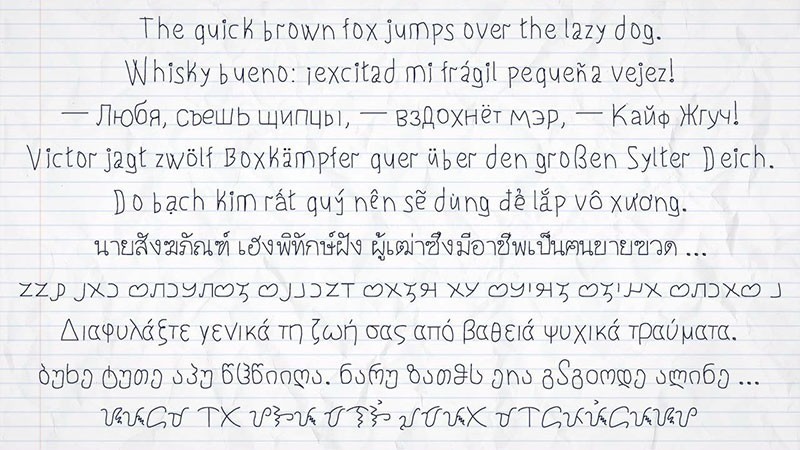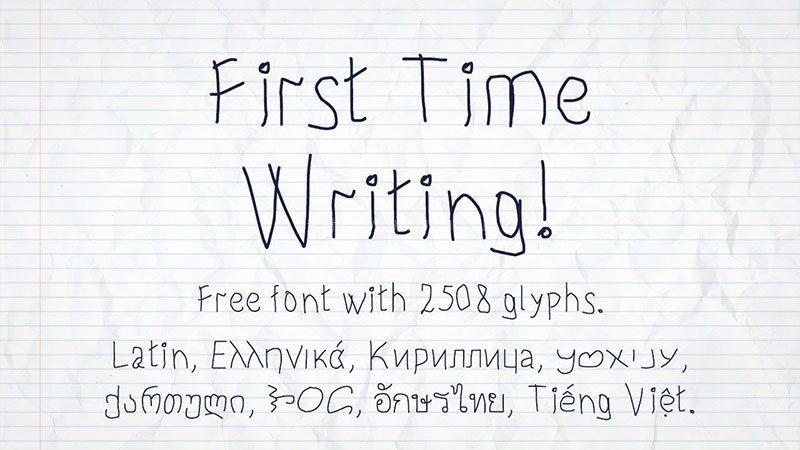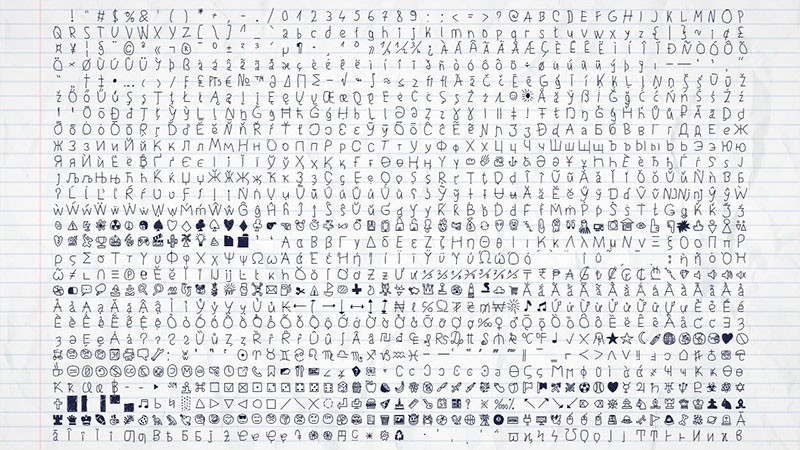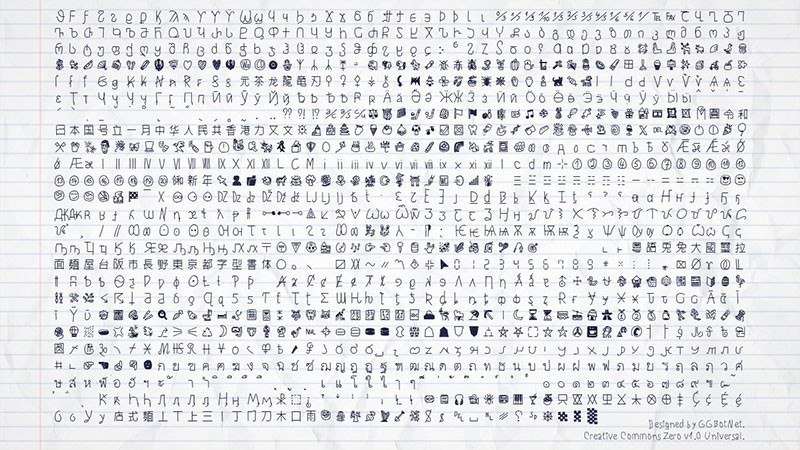
First Time Writing 免费商用儿童书写字体
这是一款专为教育领域设计的书写模仿字体,旨在还原小学初级阶段(Primary School)最基础的标准手写风格。它模仿了儿童和初学者练习时的清晰、规范字形,具备固定笔画宽度、简单结构和均匀间距,是制作教材、练习册、识字卡以及任何需要呈现易读的初学手写体内容的理想选择。包含 1024 个字形,全面支持 拉丁、西里尔和希腊字母。